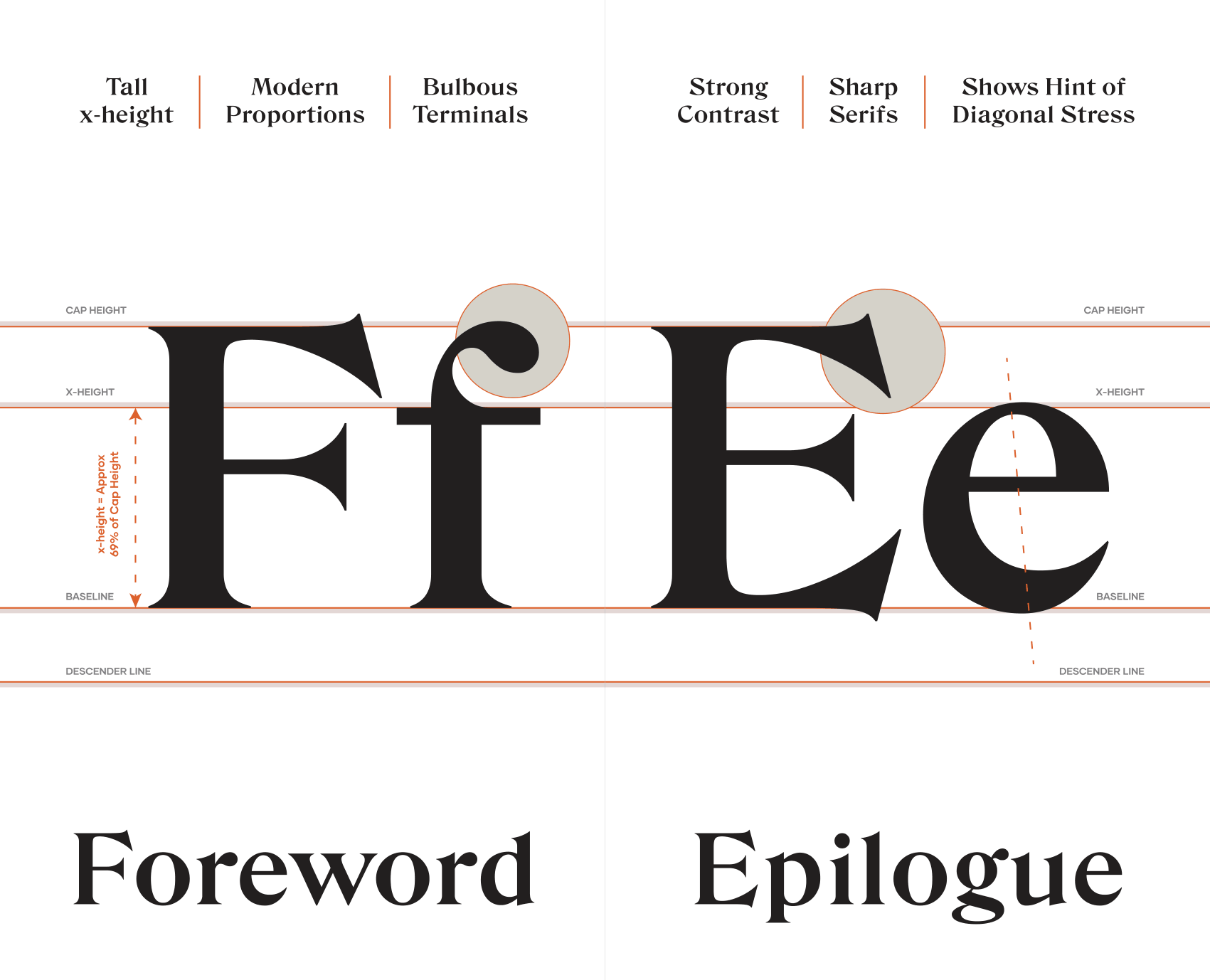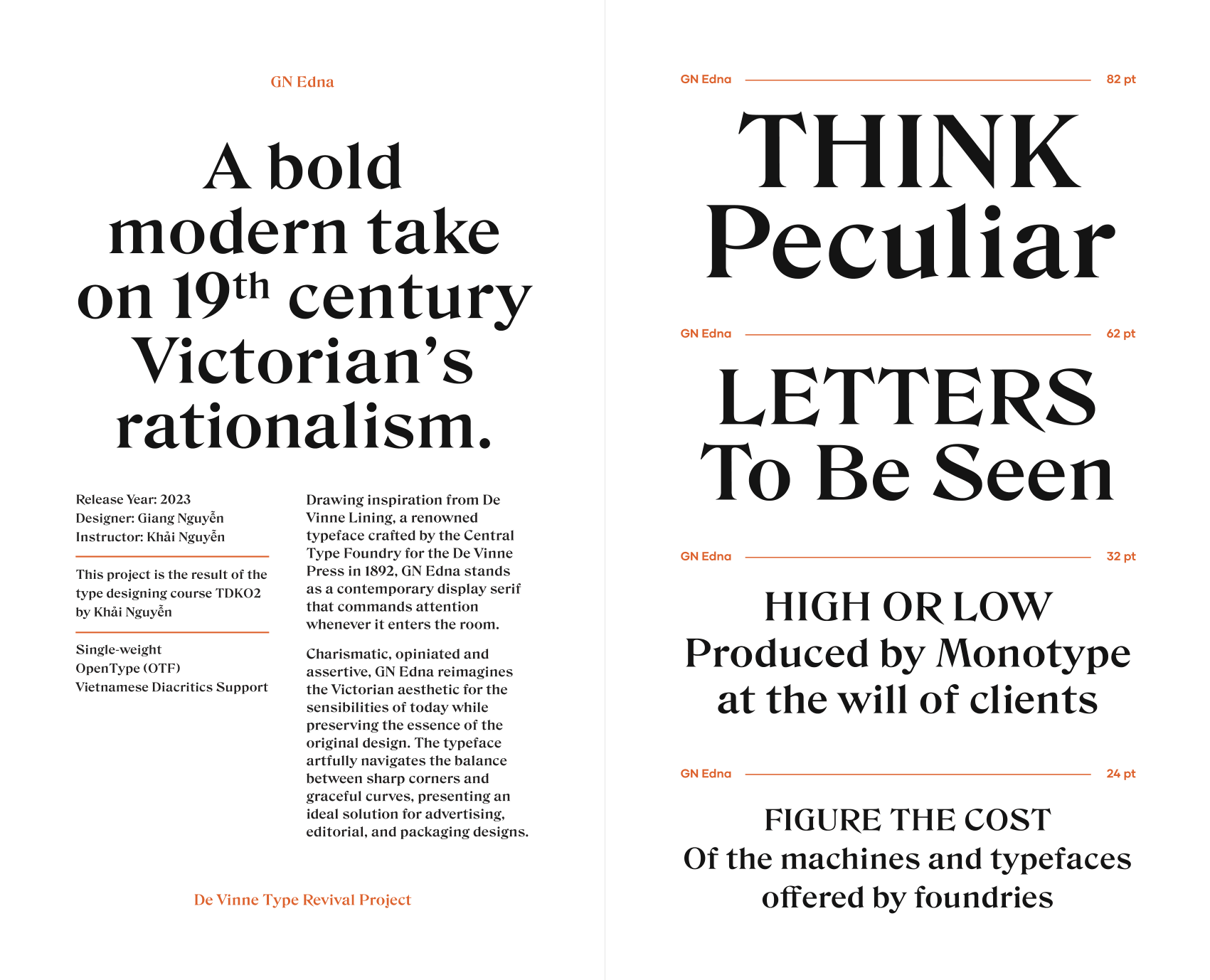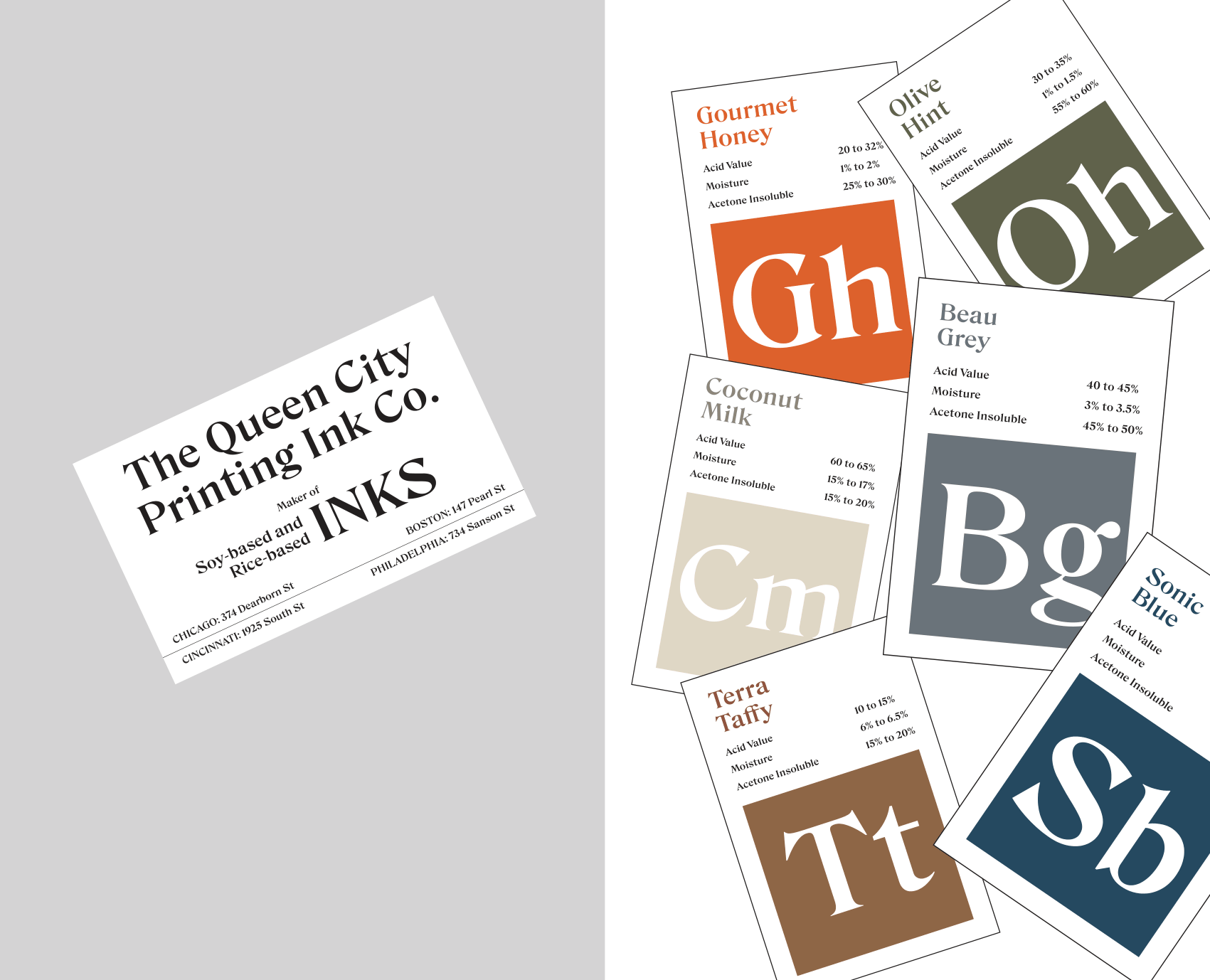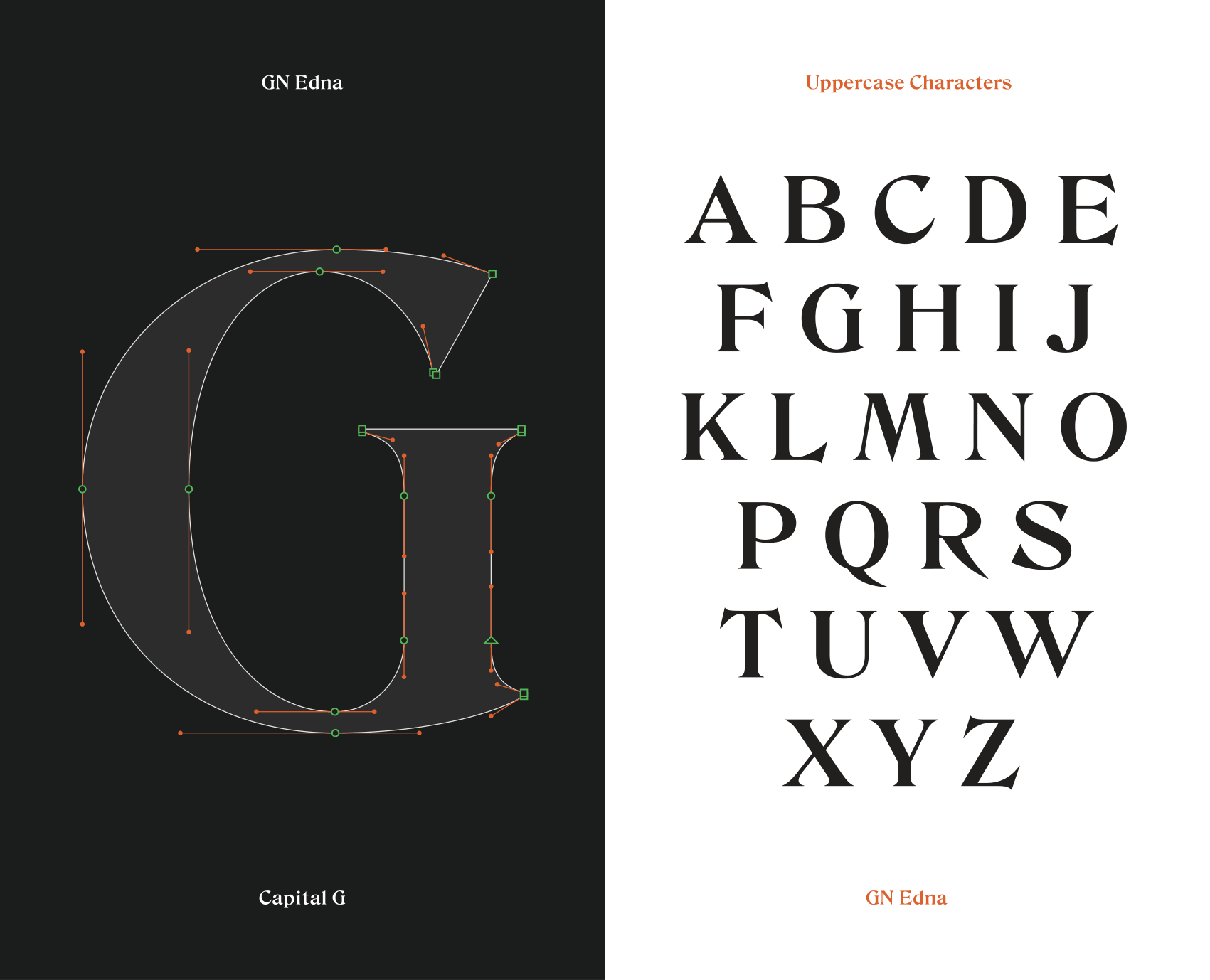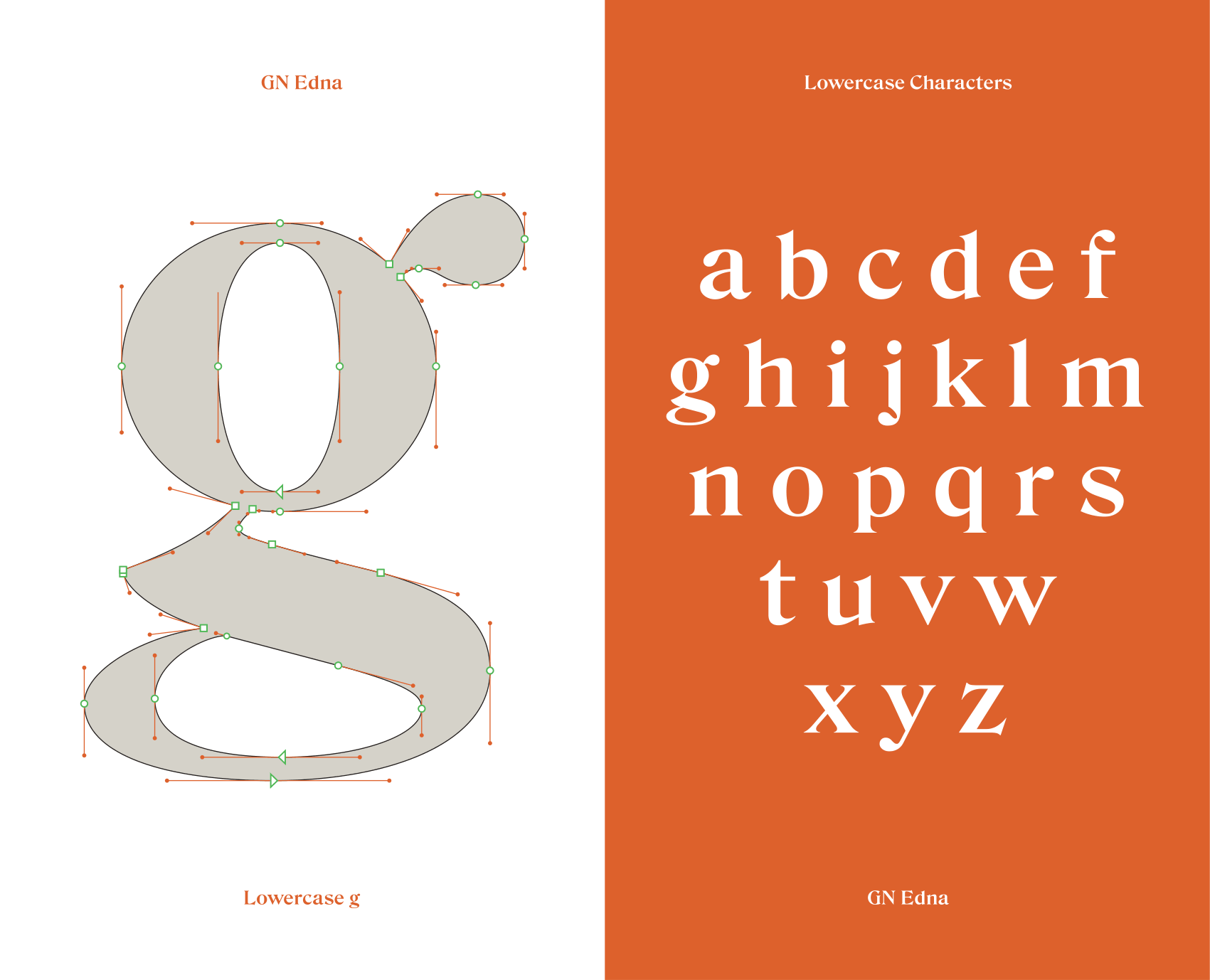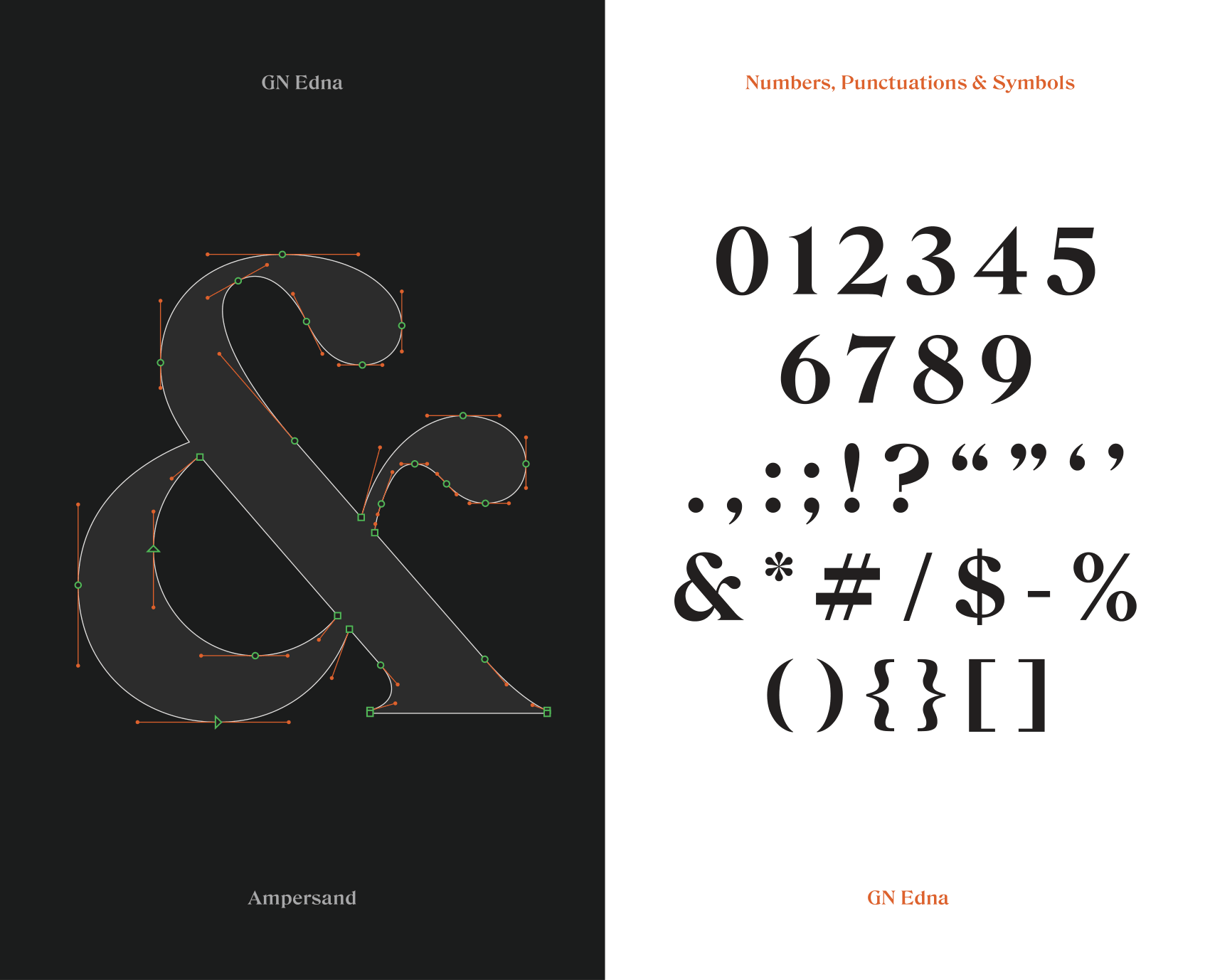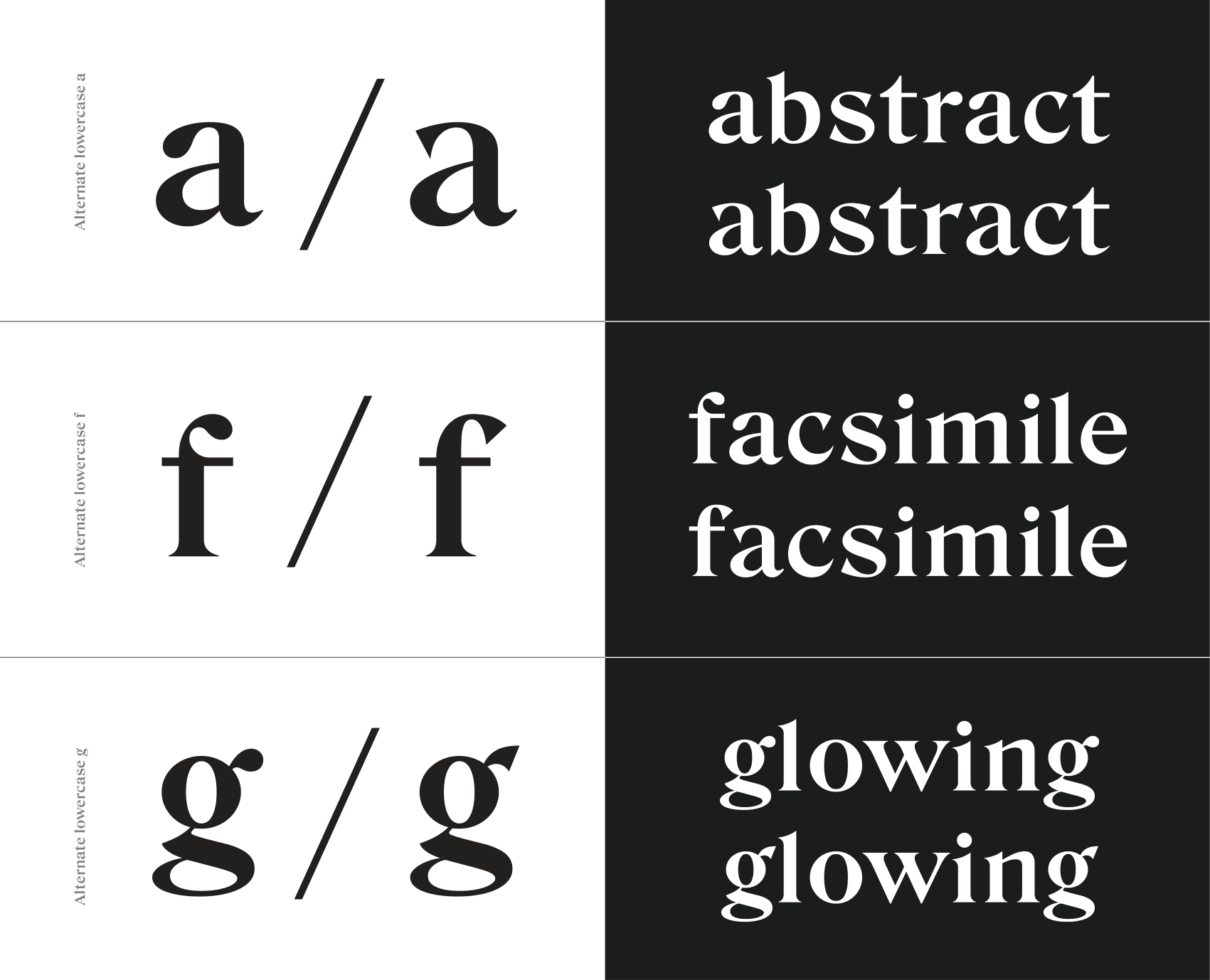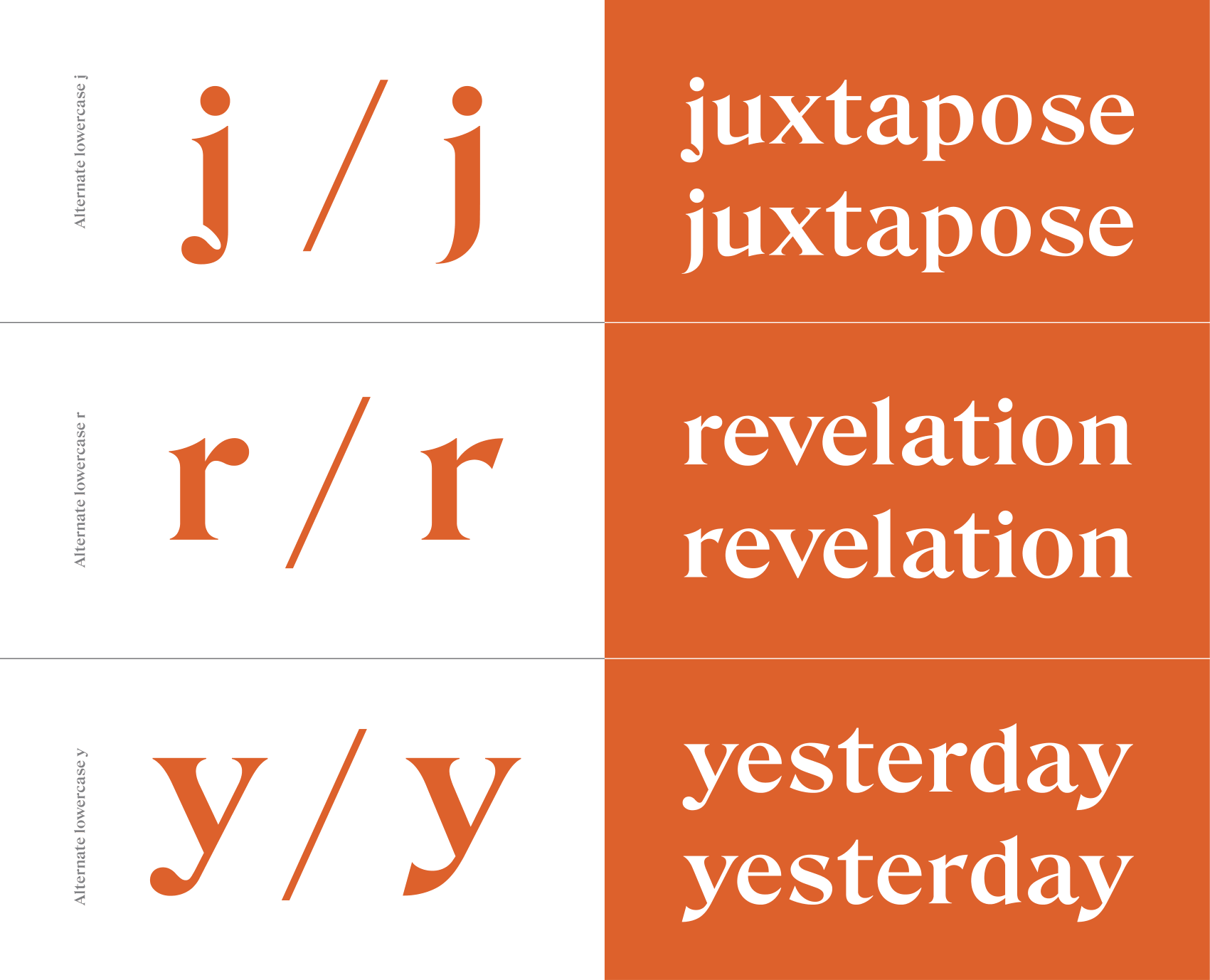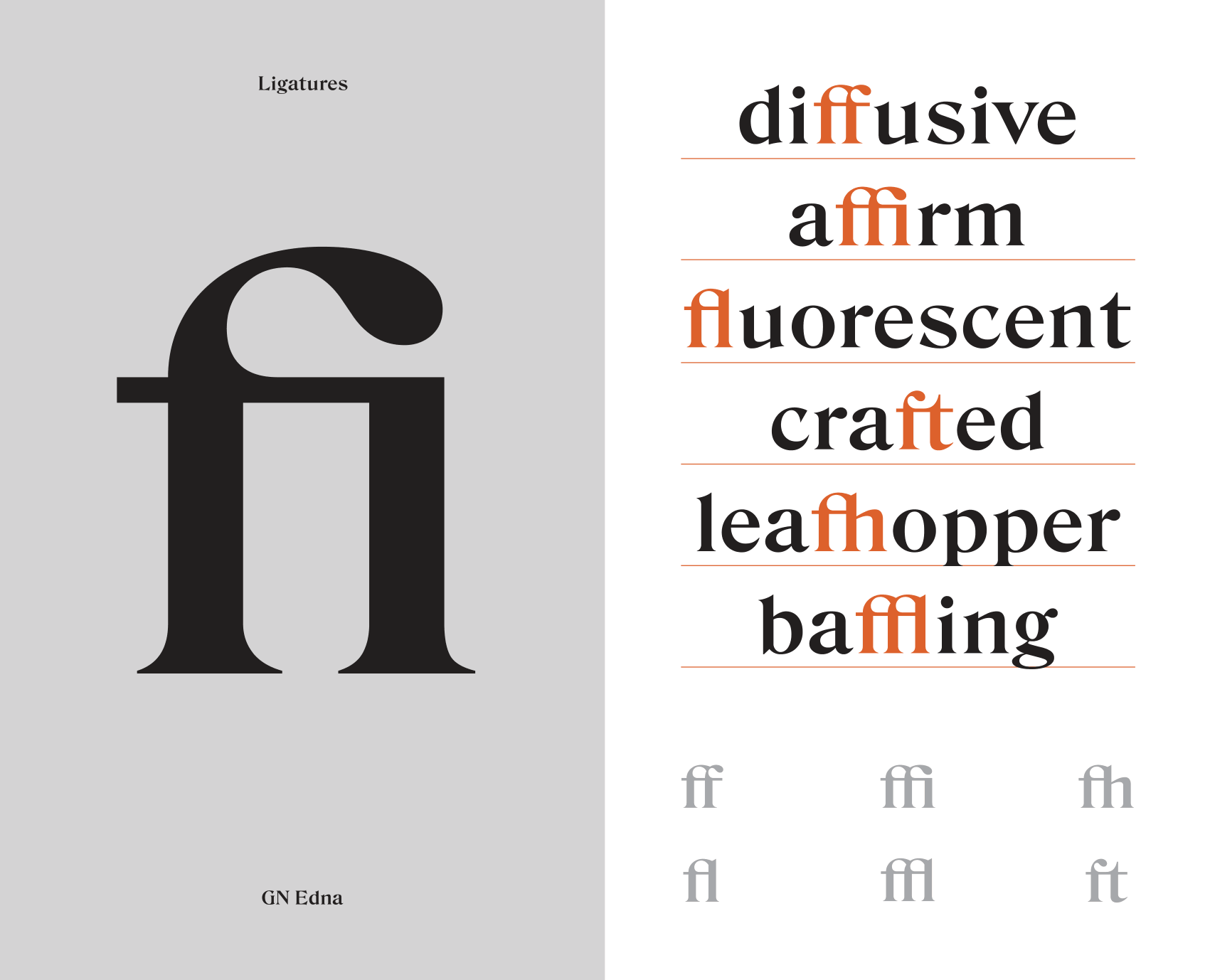
GN Edna
Về GN Edna: Lấy cảm hứng từ De Vinne Lining, một kiểu chữ nổi tiếng được Central Type Foundry thiết kế cho De Vinne Press vào năm 1892, GN Edna là một phông serif chuyên display mang cá tính, quan điểm rõ ràng và đầy quyết đoán. GN Edna tái hiện thẩm mỹ thời Victoria cho cảm quan của hiện tại, đồng thời vẫn giữ được tinh thần của thiết kế nguyên bản. Kiểu chữ này khéo léo cân bằng giữa những góc cạnh sắc nét và các đường cong mềm mại, trở thành lựa chọn lý tưởng cho các thiết kế quảng cáo, biên tập và bao bì.
Transitional Serif
Display
Giang Nguyễn
Khoá 02 | Hè 2023
GN Edna
Rational
GN Edna
Opinionated
GN Edna
Modern Epilogue
GN Edna
Unmatched Edges
GN Edna
De Vinne Lining was a commission by the prestigious De Vinne Press to the Boston-based Central Type Foundry, with a brief to create a new typeface that responded to a “need of plainer types of display, to replace the profusely ornamented types in fashion”.
GN Edna
The De Vinne Press suggested a return to the simplicity of the true old-style character, but with the added features of thicker lines and adjusted proportion in shapes of letters. De Vinne Press acquired Romische Versalien from Genzsch & Heyse and this was to be the basis of the design. While the press or its owner made no contribution to its design or production, the Central Type Foundry owners named it De Vinne to possibly honor the correspondence between the two that led to its creation. It proved to be a popular typeface that allowed for more weights and styles to be added soon after it first made its debut around 1892.